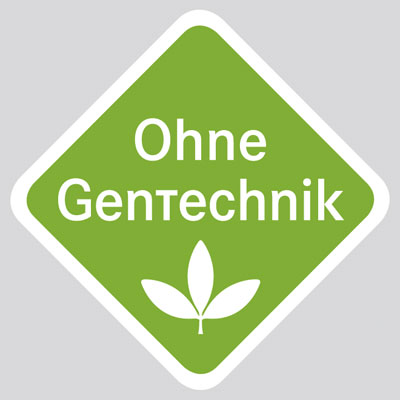
Mit der Einführung eines einheitlichen Logos »Ohne Gentechnik« (links) kommt das Bundesministerium für Ernährung, Landwirtschaft und Verbraucherschutz dem Wunsch vieler Verbraucher und der interessierten Lebensmittelwirtschaft entgegen. Zwar bestehe bereits seit Anfang 2008 die Möglichkeit, gentechnikfreie Lebensmittel mit der Angabe »ohne Gentechnik« zu kennzeichnen. Allerdings wurde in der Praxis diese Kennzeichnung bislang nur zurückhaltend verwendet.
Nach den Vorgaben des europäischen Lebensmittelkennzeichnungsrechts ist es nicht möglich, eine verbindliche Kennzeichnung für tierische Produkte wie Milch, Eier oder Fleisch einzuführen, die von Tieren stammen, die mit gentechnisch veränderten Futtermitteln gefüttert wurden. Darüber hinaus können in Lebensmitteln Spuren von gentechnisch veränderten Bestandteilen enthalten sein, ohne dass diese gekennzeichnet sein müssen. Das neue Label macht es nun möglich, diese Lücken zu schließen. Es gibt die Sicherheit, dass in den so gekennzeichneten Lebensmitteln keine gentechnisch veränderten Bestandteile, auch nicht in Spuren, vorhanden sind.
absolut lobenswerte Idee und dringend nötig, aber in der Ausführung unterdurchschnittlich. Die Ecken sind nicht angepasst sondern bilden durch den gleichen Eckenradius unangebrachte Flecken, das T von Technik ist nicht gut eingepasst (der Querbalken ist zu dünn, der Buchstabe etwas zu schmal), das c von Technik ist mies vektorisiert etc. Wieder mal ärgerlich, dass ein Bundesministerium eine gute Idee schlecht umgesetzt in die Welt entlässt.
Diesen Entwurf nochmal sauber nacharbeiten, das wäre eine Lösung, mit der alle leben könnten, aber so ist es minderwertig.
ich schließe mich christian an und finde: solche spielerein wie mit dem T haben auf einem hinweisschild nichts zu suchen.
dem ist nichts hinzuzufügen. sehr schade, dass hier vermutlich versucht wurde ein »hippes und/oder dynamisches« element einzubringen mit dem austausch des minuskel-t. :(
Das Minuskel-T finde ich gar nicht schlecht, es trennt das zusammengesetzte Wort und verhindert, dass man »gente« oder sowas liest. Der Buchstabe ist aber schludrig eingepasst.
Hat für mich aber auch einen inhaltlichen Bezug – Gentechnisch verändertes T…
Überarbeitete Version
Wenn dieses PDF euren kritischen Augen widersteht, würde ich es als Alternative hier in der Beitrag einbauen:
Finde nur ich, dass das T zu hoch ist?
… das T ist nicht zu hoch, sondern zu schmal.
Ich denke, in meinem PDF ist das T jetzt richtig (auf die Abbildung in Kommentar 7 klicken).
Interessant auch, dass das Ministerium ein miserabel skaliertes (ergo unscharfes) JPEG als „druckfähige Version“ ansieht.
oder so:
Ach iwi ist das T so oder so Schmonzenz – man stolpert immer drüber.
@Christian – ich finde bei Dir zieht die Schwerkraft alles etwas nach unten ;) Vermutlich sind da gentechnisch behandelte Produkte resistenter.
das stimmt, aber druck das mal in 8x8mm auf eine Wurstpackung, dann hält es.
Die hier gezeigte Originazeichnung kann man wohl wieder mal getrost als Entwurf vom Behörden-Reißbrett bezeichnen. Das überarbeitete Zeichen ist schon viel besser, bloß das „T“ bleibt echt affig – das als ein „Minuskel-T“ zur verbesserten Lesbarkeit umzudeuten ist ja wohl ausgemachter Quatsch (sorry Christian). Ein „Minuskel-T“ wäre für mich immer noch ein „t“, oder irre ich mich da? Für alle, denen „Gentechnik“ ein zu kompliziertes Wort ist, könnte man ja mit der Schreibweise „Gen-Technik“ entgegenkommen … Mit dem Begriff „Gentechnik“ verbinde ich visuell ja immer eine m.o.w. abstrahierte Darstellung der „DNA-Strickleiter“, aber so ein Icon wird wahrscheinlich von den wenigsten richtig gelesen und weckt eher die gegenteiligen Assozationen. Insofern ist dieses harmlose 3-blättrige Pflänzchen auf grünem Grund schon ganz in Ordnung …
Ich hab dieses “Ding” heute morgen schon auf sueddeutsche.de gesehen und frage mich schon den ganzen Tag was dieses “T” für einen Sinn haben soll? Ein “Gentechnisch verändertes T”? Aber genau das soll es ja nicht sein, es soll ja Gentechnik frei sein!? Ich kapiers nicht…
das T ist in der tat komisch. ich habe zuerst gedacht, dass es vielleicht damit zusammenhängt, dass das wort Gen-Technik heißt und man nach einer lösung geschaut hat, das wort ohne bindestrich zu schreiben. aber es wird laut duden zusammen geschrieben. Gentechnik / GenTechnik. sieht eher aus wie ein logo von irgend ner genmanipulationsfirma aus nem science fiction film.
Dieses völlig deplatzierte “T” ist mal wieder der beste Beweis dafür, wie völlig inkompetent öffentlilche Stellen und Ministerien mit Typografie umgehen. Ich schäme mich für diese Regierung, die nicht einmal imstande ist, sich für ein millionenfach zu druckendes Logo, das auf zahlreichen Verpackungen stehen wird, kompetente Beratung einzuholen. Jeder Erstsemester mit Grafikgrundkenntnissen würde von diesem Logo abraten.
Also ich bin bei jedem Blick auf das Logo verunsichert. Warum ein dreiblättriger Gummibaumzweig? Wie Kommentator #26 habe ich auch ein fünffingriges Blatt im Hinterkopf. Und das t fällt auf meinem Superdickmanns-Karton doch gar nicht auf.
Das T ist doch ganz leicht zu verstehen: Da wird das Thema der Manipulation durchgespielt.
Zu dem Logo kann man an sich nur sagen: Profis arbeiten anders!